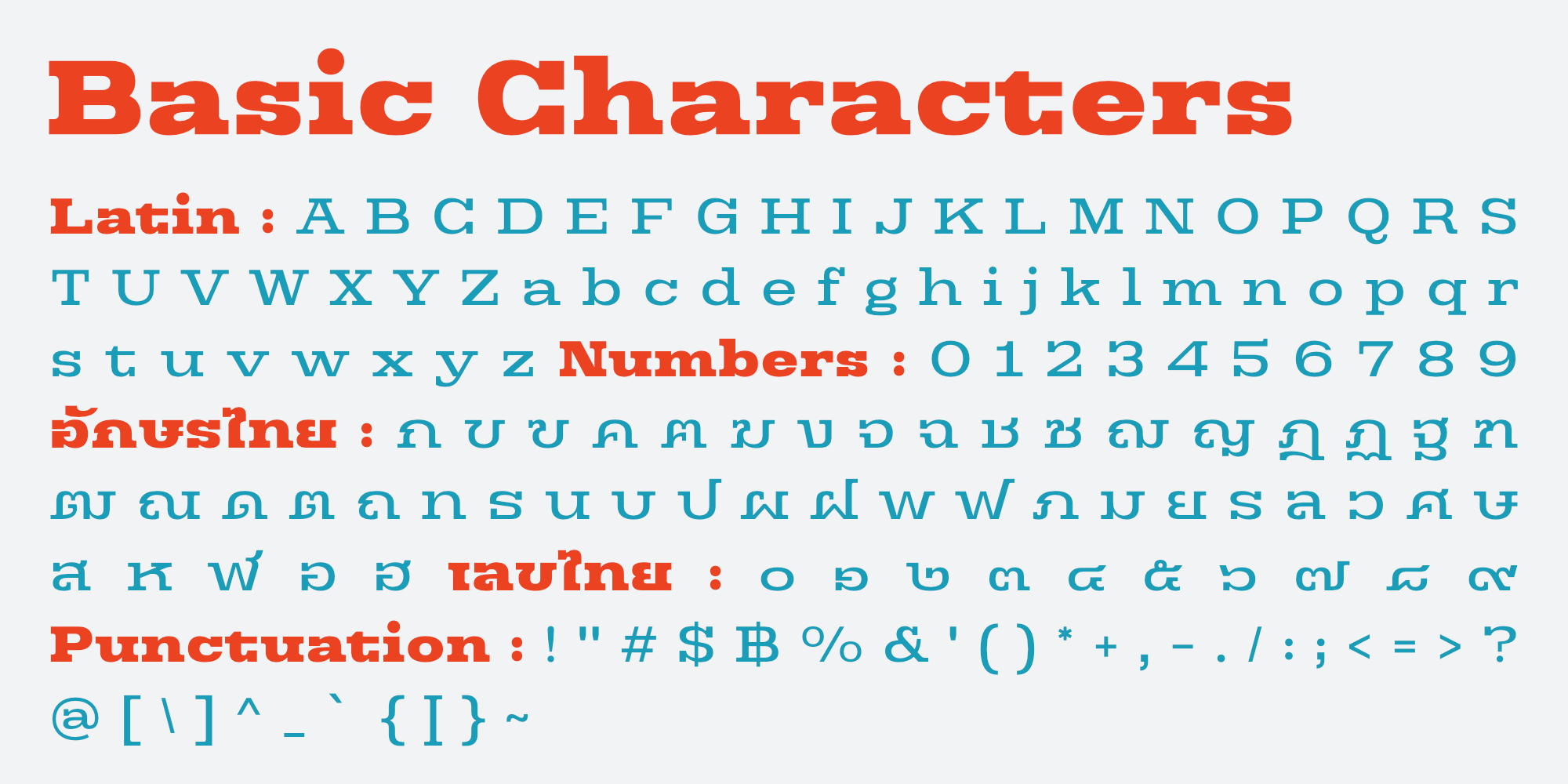
ชื่อฟอนต์ : ทวิลักษณ์ สลับ | Thawilak Slab
ขอแนะนำ "Tawilack Slab" ฟอนต์ serif แบบ slab ที่แสดงถึงความแข็งแกร่งและความมั่นคง ทวีลักษณ์ สลับ มีรูปทรงกว้าง แข็งแรงและมั่นคง คอนทราสต์ต่ำทำให้เกิดความกลมกลืนระหว่างเส้นหนาและเส้นบาง ทำให้ได้แบบอักษรที่สวยงามและอ่านง่าย ด้วยรูปลักษณ์ที่โดดเด่น ทวีลักษณ์ สลับ จึงสมบูรณ์แบบสำหรับโปรเจ็คที่ต้องการความชัดเจนและมั่นใจ ไม่ว่าจะใช้พาดหัว หรือสร้างแบรนด์ Thawilack Slab ก็สร้างความประทับใจได้ไม่รู้ลืมด้วยรูปลักษณ์ที่แข็งแกร่งและมั่นคงดึงดูดความสนใจ แบบอักษรนี้เป็นตัวเลือกอเนกประสงค์ที่สามารถปรับเข้ากับบริบทการออกแบบต่างๆ ได้อย่างลงตัว ทำให้เป็นคู่หูที่ยอดเยี่ยมสำหรับทั้งสิ่งพิมพ์และสื่อดิจิทัล
Introducing "Thawilack Slab," a captivating slab serif font that exudes strength and stability. Thawilack Slab boasts a wide and sturdy shape, radiating strength and stability. Its low contrast creates a harmonious flow between the thick and thin strokes, resulting in a visually pleasing and easily readable typeface. With its commanding presence, Thawilack Slab is perfect for projects that require a bold and confident touch. Whether used for headlines, or branding materials, Thawilack Slab leaves a lasting impression. Its strong and stable appearance captures attention. This font is a versatile choice that adapts seamlessly to various design contexts, making it an excellent companion for both print and digital media.